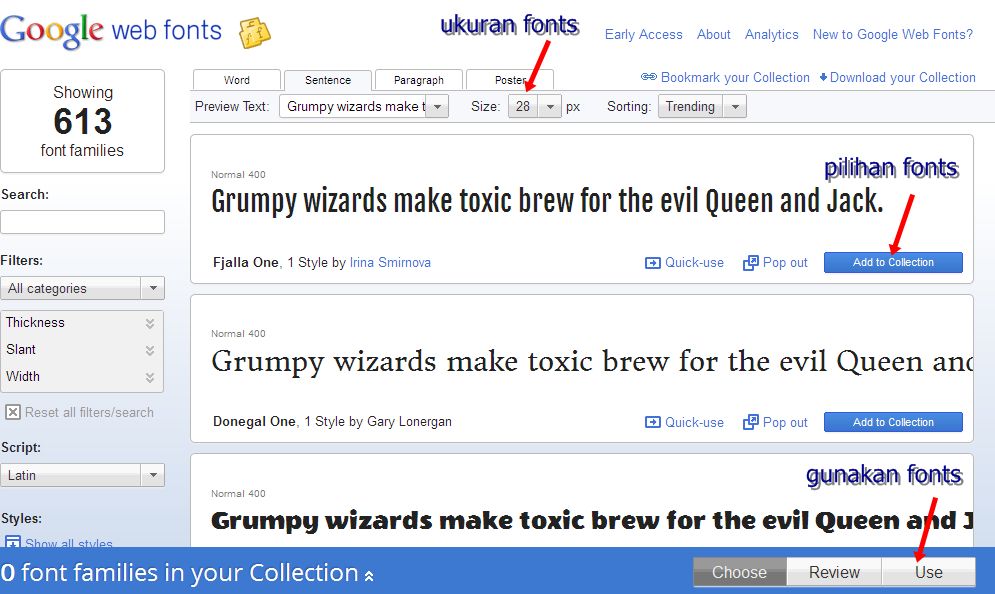
В первой статье модуля, мы изучали основные функции CSS доступные для стилизации шрифтов и текста. В этой статье мы продвинемся дальше изучая веб-шрифты в деталях — они позволяют вам загружать пользовательские шрифты вместе с вашей веб-страницей, чтобы обеспечить более разнообразный, индивидуальный стиль текста.
Как мы рассматривали в Фундаментальной стилизации текста и шрифта, шрифты примененные к вашему HTML могут контролироваться при помощи свойства font-family. Оно принимает одно и более имен семейств шрифтов и браузер следует по списку пока не найдет тот шрифт, который является доступным в системе, под управлением которой он работает:
p {
font-family: Helvetica, "Trebuchet MS", Verdana, sans-serif;
}Эта система работает хорошо, но традиционно выбор шрифтов веб-разработчиков была ограниченной.
Существует только горсть шрифтов которые вы можете гарантировать, что они являются доступными во всех распространенных системах — так называемые Безопасные веб-шрифты. Вы можете использовать стек шрифта для указания предпочтительных шрифтов, за которыми следует веб-безопасные альтернативы, за которыми следует системный шрифт по умолчанию, но это добавляет дополнительной работы с точки зрения тестирования, чтобы убедиться, что ваш дизайн выглядит хорошо с каждым из шрифтов и т. д.
Но есть альтернатива, которая работает очень хорошо начиная с 6-ой версии IE. Веб-шрифты — это функция CSS позволяющая вам указывать файлы шрифтов, загружаемые вместе с вашим веб-сайтом по мере доступа к нему, это означает, что любой браузер, поддерживающий веб-шрифты, может иметь в своем распоряжении именно те шрифты, которые вы укажете. Замечательно! Требуемый синтаксис выглядит примерно так:
Во-первых, у вас есть блок @font-face в начале CSS, который указывает файл(-ы) шрифтов для загрузки:
@font-face {
font-family: "myFont";
src: url("myFont.
woff");
}Ниже вы можете использовать имя семейства шрифтов, указанное внутри @font-face, чтобы применить свой собственный шрифт ко всему, что вам нравится, как обычно:
html {
font-family: "myFont", "Bitstream Vera Serif", serif;
}Синтаксис становится немного сложнее, чем этот; мы вдадимся в подробности ниже.
Есть две важные вещи, которые нужно иметь в виду о веб-шрифтах:
- Браузеры поддерживают разные форматы шрифтов, поэтому вам будут нужны несколько форматов шрифтов для приличной кросс-браузерной поддержки. Например, большинство современных браузеров поддерживают WOFF/WOFF2 (Web Open Font Format versions 1 and 2), наиболее эффективный формат, но старые версии IE поддерживают только шрифты EOT (Embedded Open Type) и вам возможно понадобиться включать версию SVG шрифта для поддержки старых версий браузеров iPhone и Android. Ниже мы покажем вам как генерировать требуемый код.
Имея это в виду, давайте создадим базовый пример веб-шрифта из первых принципов. Сложно продемонстрировать это на встроенном живом примере, поэтому вместо, мы бы хотели, чтобы следовали детальным шагам в секциях ниже, чтобы понять идею процесса
Вы должны использовать файлы web-font-start.html и web-font-start.css как отправную точку добавляя в них ваш код (см. живой пример). Сейчас сделайте копию этих файлов в новой директории на вашем компьютере. В файле вы найдете некоторый минимальный CSS для работы с базовым макетом и версткой примера.
Поиск шрифтов
В этом примере мы будем использовать два веб-шрифта, один для заголовков, и другой для основного текста.
Для того чтобы начать нам необходимо найти файлы шрифтов, которые содержат эти шрифты. Шрифты созданы шрифтовыми «цехами» и хранятся в разных форматах фалов. Как правило существует три типа сайтов, где вы можете получить шрифты:
- Бесплатный дистрибьютер шрифтов: это сайт, который предоставляет бесплатные шрифты для скачивания (могут существовать некоторые условия лицензии, например, указание создателя шрифта). Примеры включают Font Squirrel, dafont, и Everything Fonts.
- Платный дистрибьютер шрифтов: это сайт, который предоставляет шрифты за плату, например fonts.com или myfonts.com. Также вы можете купить шрифты напрямую у производителя шрифтов, например Linotype, Monotype, или Exljbris.
- Сервис онлайн шрифтов: это сайт, который предоставляет вам шрифты, делая весь процесс проще. Смотрите раздел Использование онлайн-сервиса шрифтов для более подробной информации.
21. Signika
Бесплатный веб-шрифт Signika был разработан с учетом ясности В традициях, заложенных такими людьми, как Мета и Тахома, Анна Гедри разработала Signika с вывесками и ориентированием, где ясность является ключевым фактором.Этот бесплатный веб-шрифт представляет собой шрифт без засечек с низким контрастом и высокой высотой по оси x, качество, которое хорошо отображается на экране. Его широкий набор символов включает в себя заглавные буквы, пиктограммы и стрелки.
22. Josefin Slab